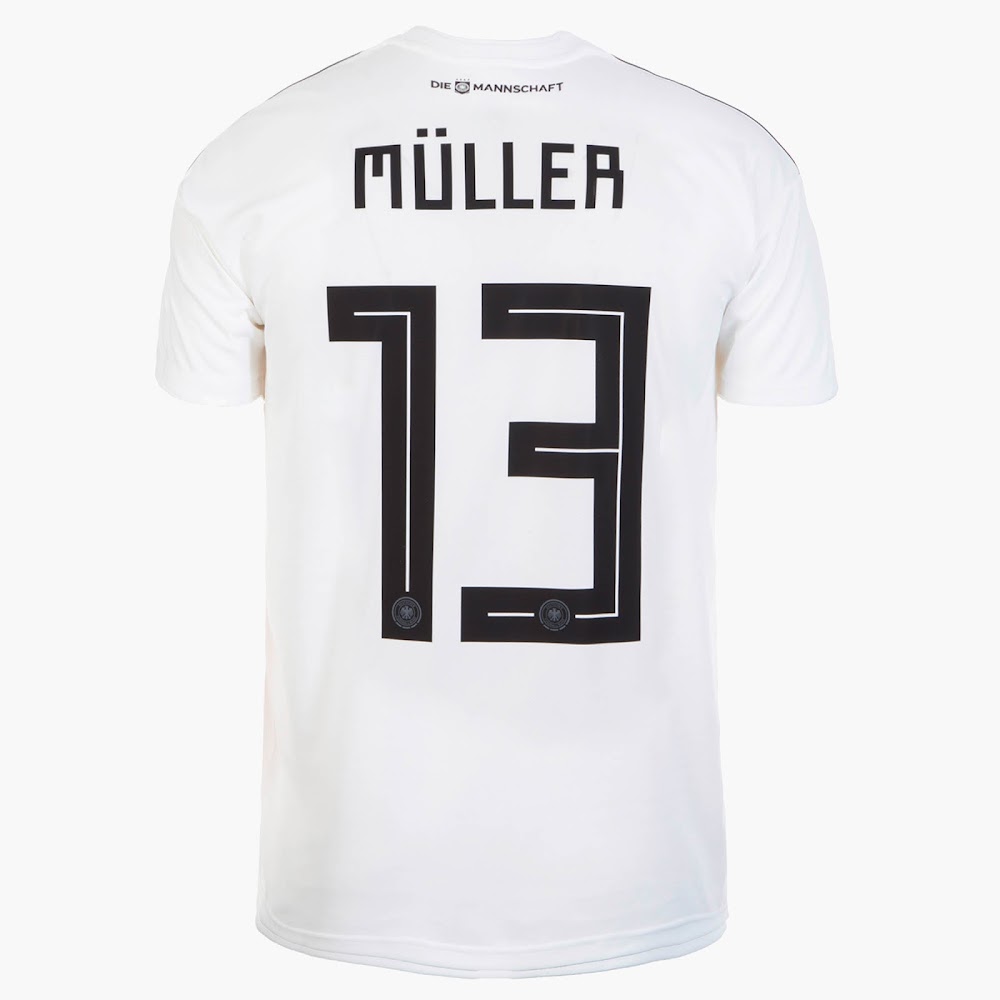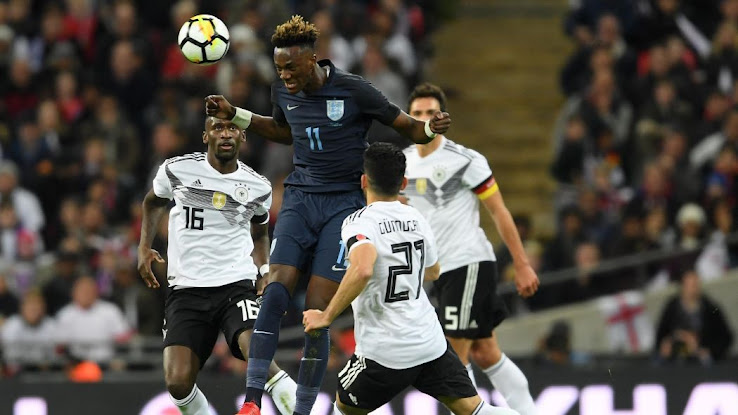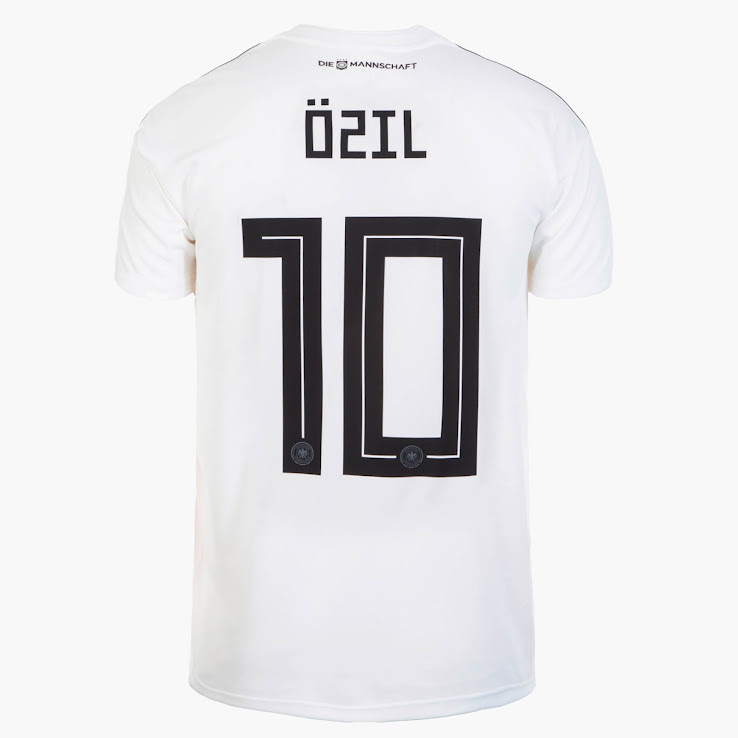
Vollständige Adidas WM 2018 Schriftart veröffentlicht
Über die letzten Tage hinweg haben Adidas-Teams ihre WM 2018 Heimtrikots debütiert. Wir werfen einen näheren Blick auf die offizielle Adidas-Schriftart für die WM 2018, die von der traditionellen sowjetischen Symbolik inspiriert wurde.
Adidas WM 2018 Schriftart
Diese Bilder zeigen einige Beispiele der Schriftart.
Die Adidas WM 2018 Schriftart, die für alle Adidas-Teams verwendet wird, von Argentinien und Kolumbien zu Deutschland und Spanien, hat einen sehr deutlichen Look.
Die Schriftart, die stark von traditioneller sowjetischer Symbolik inspiriert wurde, hat gewissermaßen einen rohen und ausgeschnittenen Stil. Die Schriftart enthält keine Art Rundung und weist nur 90-Grad-Winkel auf. Zu guter Letzt verläuft eine dünne Linie durch das Zentrum der Zahlen.
Vollständiger Blick auf die Adidas WM 2018 Schriftart von Samarony Lima - Bitte beachte, dass manche Buchstaben (z.B. Z) falsch sind.